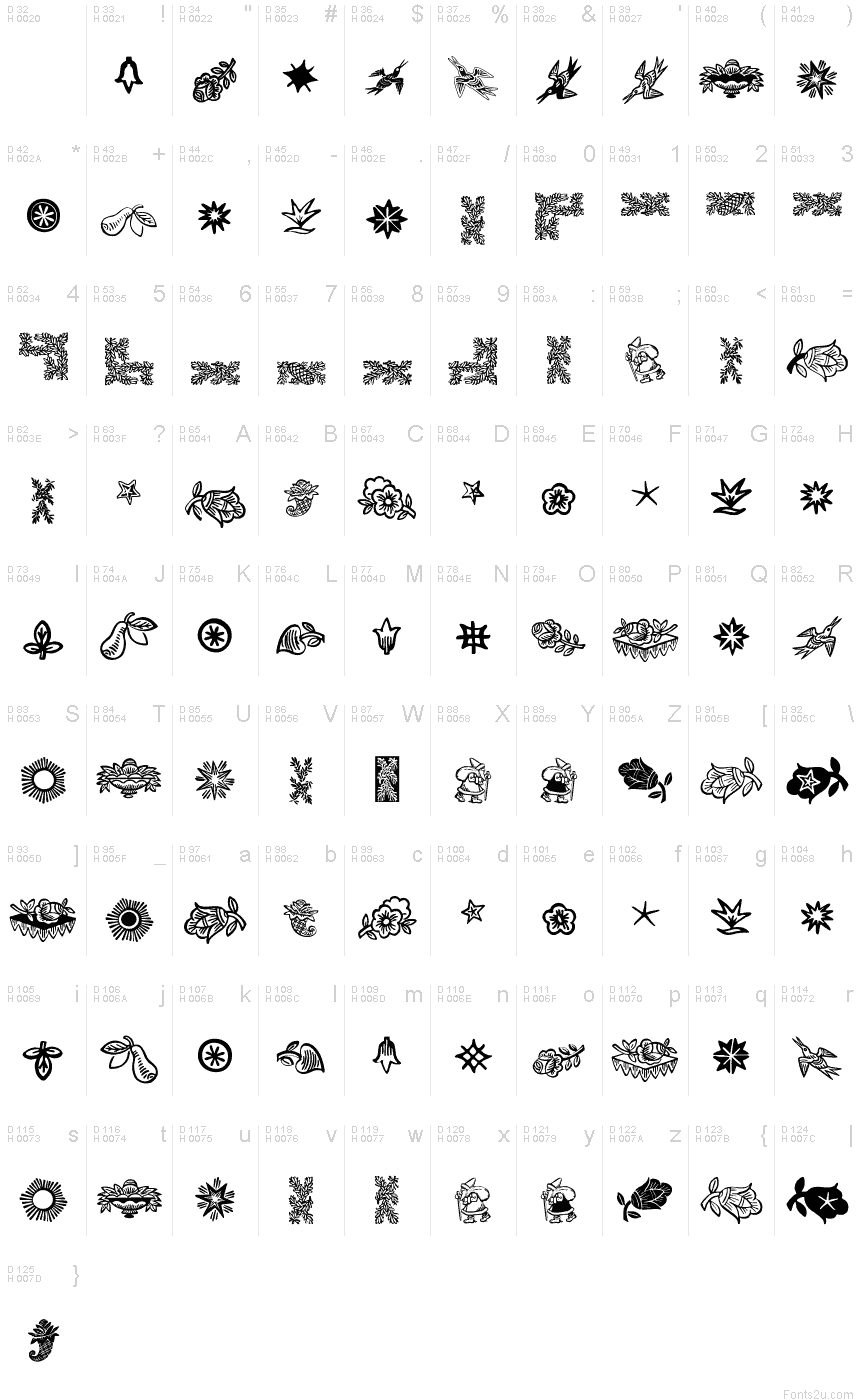
DeutscherSchmuck von Eduard Ege für Genzsch & Heyse ist ein kostenloses Ornament-Set, bestehend aus kräftigen, tintenartigen Sternen und floralen Symbolen. Die Formen wirken fast geschnitzt und leicht unregelmäßig; ihre massiven schwarzen Flächen und scharfen Strahlen verleihen jedem Zeichen einen haptischen Letterpress-Charakter, anstatt eines glatten Vektor-Looks.
Diese kostenlose Schrift ist ideal für kompakte dekorative Akzente in Ihren Layouts – ob für Einladungen, Urkunden, Vintage-Poster, Trennlinien in Menüs, Verpackungs-Badges, Kapitelumbrüche oder Boutique-Logos. Da die Symbole sehr dunkel und dicht wirken, harmoniert DeutscherSchmuck am besten mit einer ruhigen Serifenschrift oder einer Fraktur in kleineren Größen. So fungieren die Ornamente als markante Hingucker, ohne dem eigentlichen Text die Show zu stehlen.
Eduard Ege for Genzsch & Heyse, Muenchen 1922. Digitized by Manfred Klein and Petra Heidorn.
DeutscherSchmuck
Nach Zeichnungen des Grafikers Eduard Ege in Muenchen als Zusatz zur Deutschen Druckschrift von Heinz Koenig.